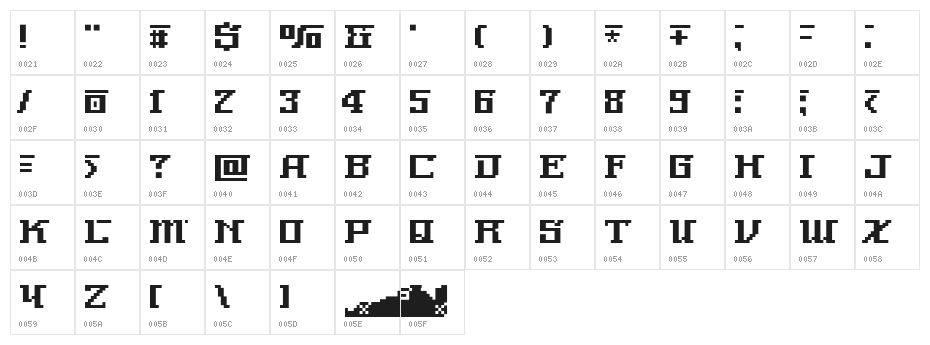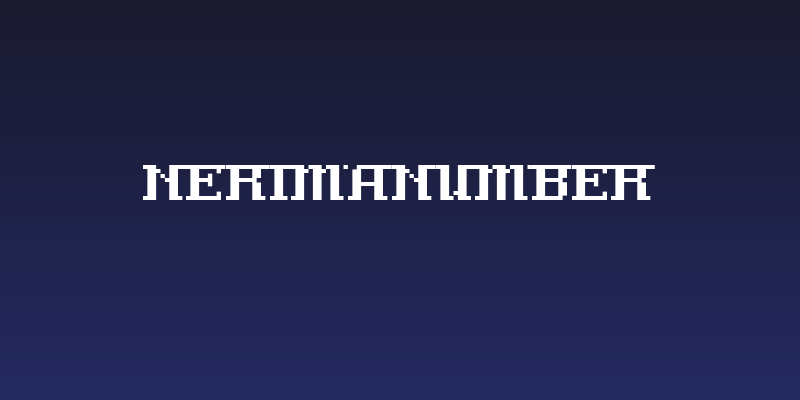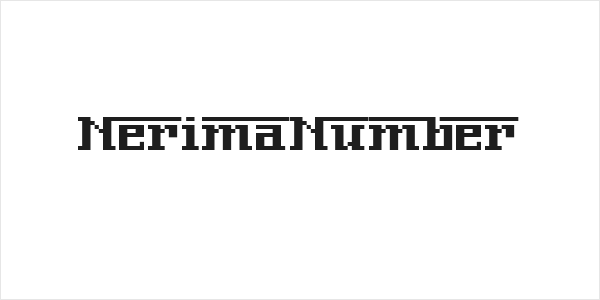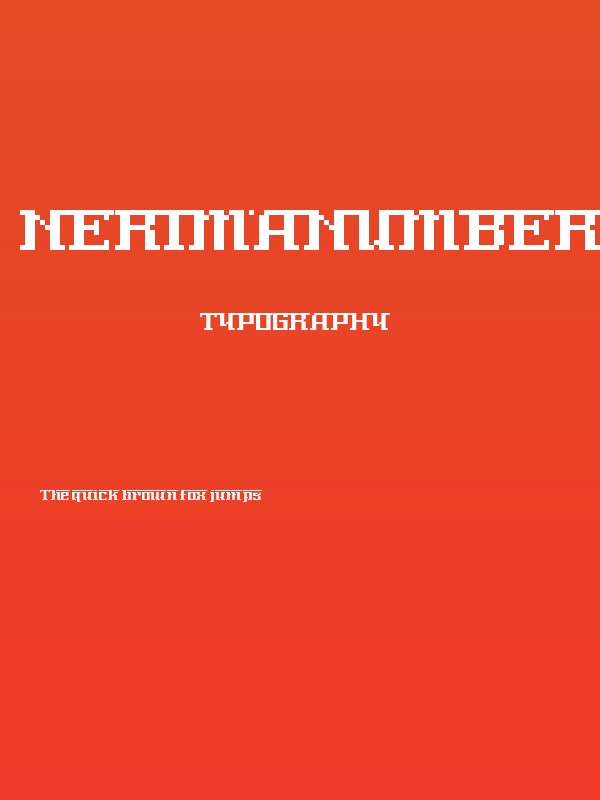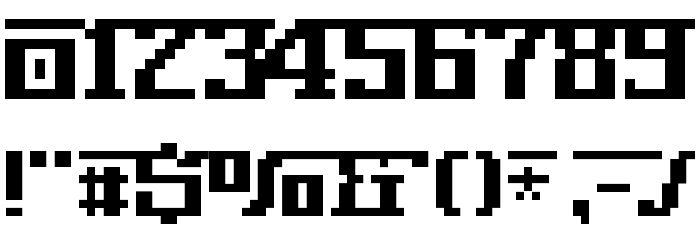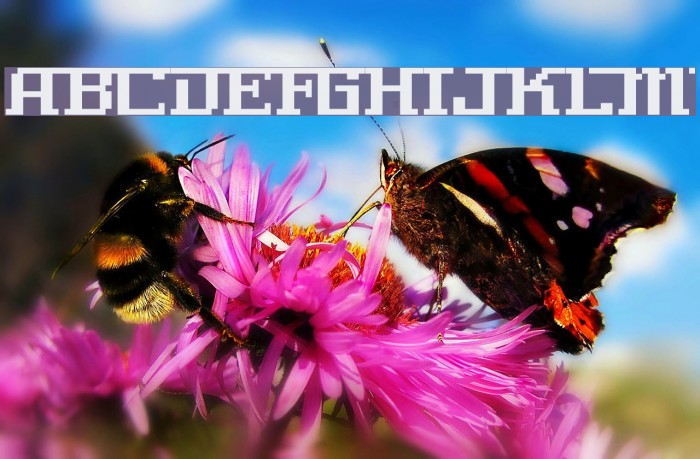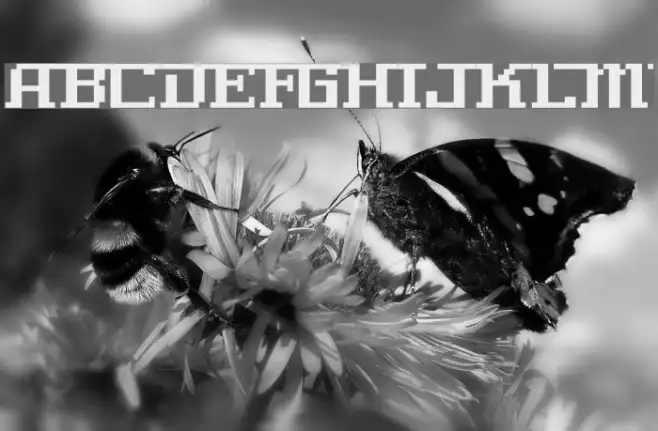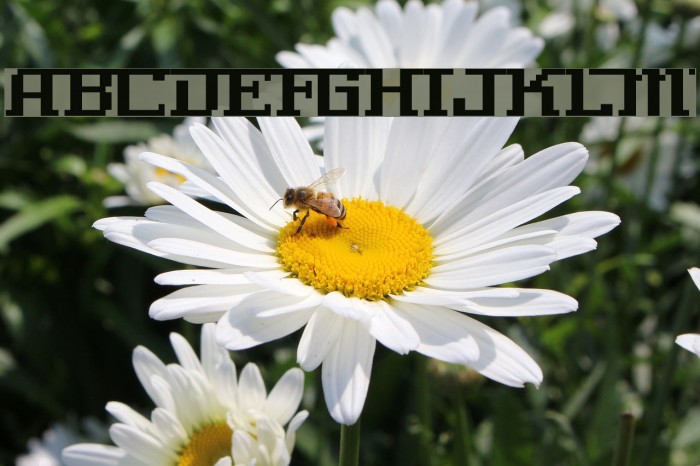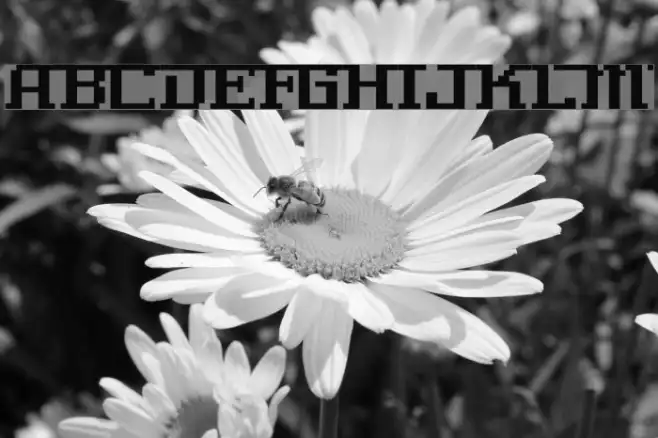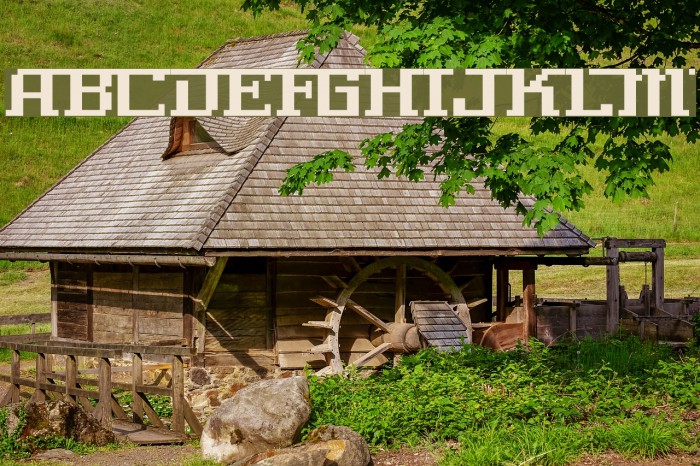
NerimaNumber Font
| Style général | Retro, Digital |
| Projets proposés | Ideal for projects that require a retro or digital theme, such as video game graphics, tech-themed posters, or digital art. |